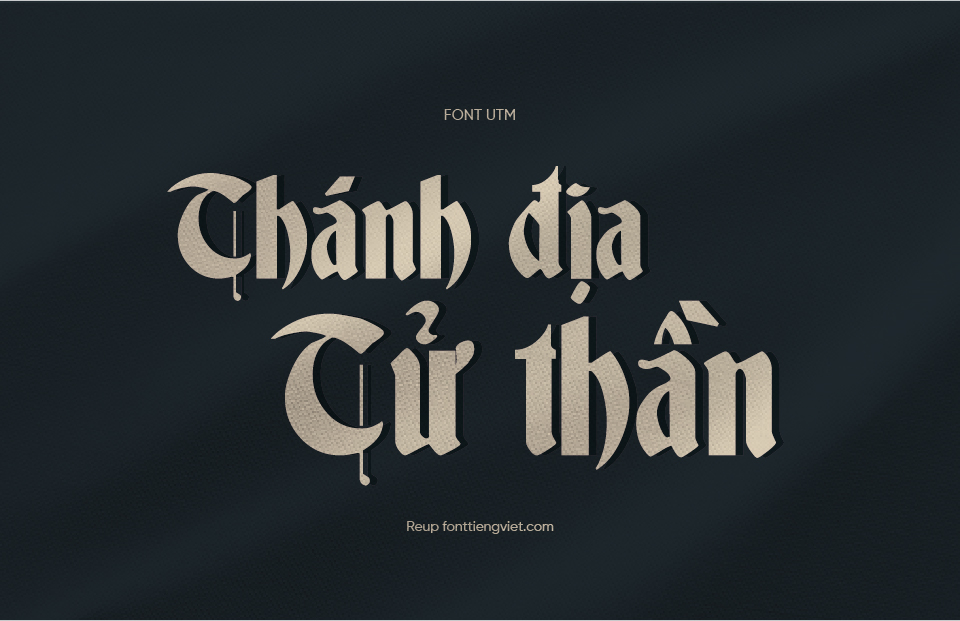
Giới thiệu về Font việt hóa UTM Deutsch Gothic
Trong thế giới thiết kế đồ họa hiện nay, việc tìm kiếm một Font Chữ vừa mang nét cổ điển vừa hiện đại là điều không hề dễ dàng. Font việt hóa UTM Deutsch Gothic chính là sự lựa chọn hoàn hảo cho những ai yêu thích phong cách chữ Gothic mạnh mẽ và đầy cá tính. Được chuyển ngữ tỉ mỉ bởi đội ngũ UTM, bộ phông này giúp người dùng Việt Nam dễ dàng sử dụng trong các phần mềm thiết kế phổ biến mà không lo lỗi hiển thị bảng mã. Đây là giải pháp tối ưu cho các dự án yêu cầu sự trang trọng, bí ẩn và khác biệt.
Đặc điểm nổi bật của bộ chữ UTM Deutsch Gothic
Bộ Font việt hóa UTM Deutsch Gothic sở hữu những đường nét góc cạnh, sắc sảo, gợi nhớ đến phong cách kiến trúc và nghệ thuật châu Âu thời trung cổ. Các ký tự được tinh chỉnh để giữ nguyên linh hồn của bản gốc nhưng vẫn đảm bảo tính cân đối và dễ đọc khi hiển thị tiếng Việt. Với định dạng linh hoạt, người dùng có thể áp dụng font này vào nhiều mục đích khác nhau từ in ấn đến trình chiếu kỹ thuật số.
Ứng dụng thực tế của Font việt hóa UTM Deutsch Gothic
Lĩnh vực phù hợp cho phong cách Gothic
Nhờ vẻ ngoài độc đáo, Font việt hóa UTM Deutsch Gothic thường được ưu tiên sử dụng trong thiết kế bìa sách, poster phim cổ trang, hoặc các biểu tượng thương hiệu đòi hỏi sự uy quyền. Ngoài ra, trong môi trường giáo dục, các bạn học sinh có thể dùng bộ phông này để trang trí bài thuyết trình, làm thiệp chúc mừng hoặc tiêu đề báo tường nhằm tạo ấn tượng thị giác mạnh mẽ với người xem.